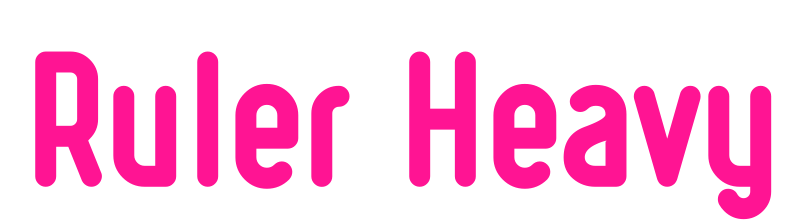
Ruler Heavy 詳情頁
字體名稱: Ruler H
Ruler Heavy
Ruler Heavy字體字庫是一款讓人賞心悅目、百看不厭的英文字體,適合各類廣告和產(chǎn)品包裝設(shè)計(jì)應(yīng)用,字體大小0.04MB,格式為ttf字體,上傳用戶是白刃寒走得慢,作者/版權(quán)方為未知